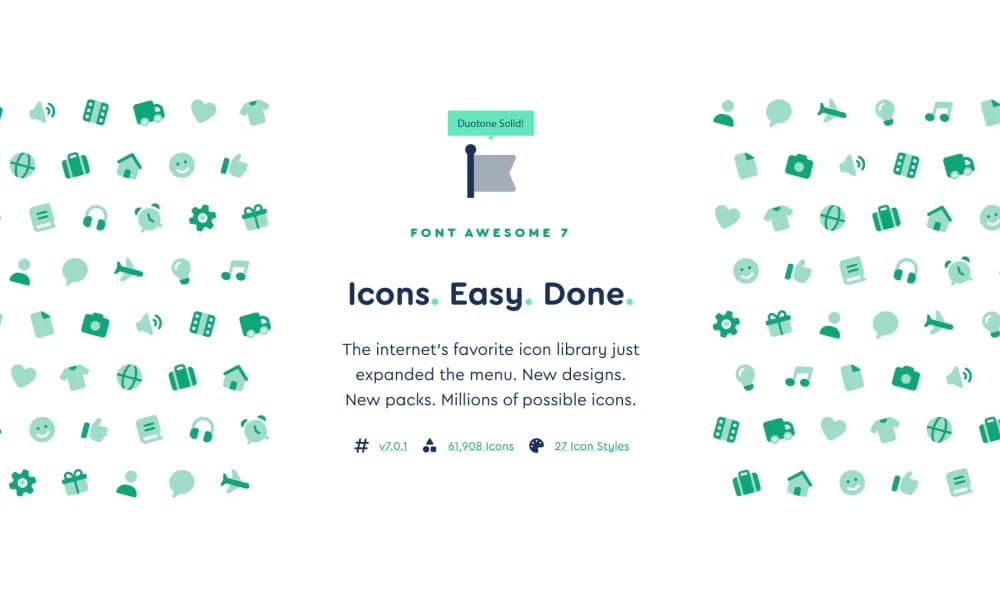
Descripción General
Font Awesome es uno de los kits de herramientas de iconos más populares y ampliamente utilizados del mundo. Proporciona un conjunto masivo e integral de iconos vectoriales que cubren casi todos los casos de uso, que pueden integrarse fácilmente en sitios web y aplicaciones mediante fuentes web o SVG. Una biblioteca de iconos masiva e integral: Con decenas de miles de iconos, Font Awesome es un 'cofre del tesoro definitivo' donde casi siempre puedes encontrar lo que necesitas. Su colección abarca desde iconos comunes de UI hasta una amplia gama de símbolos para negocios, branding, medicina, transporte y otras industrias específicas. Fácil de integrar para desarrolladores: La integración es increíblemente simple. Incluyendo un solo archivo CSS, puedes invocar iconos con una simple etiqueta HTML (como <i class='fa-solid fa-house'></i>) y darles estilo con CSS igual que al texto, controlando tamaño, color, sombras y más. Múltiples estilos con alta consistencia: Ofrece una variedad de estilos diseñados profesionalmente, incluyendo Solid, Regular, Light, Thin y un estilo único Duotone. Todos los estilos mantienen un alto grado de consistencia visual en toda la biblioteca. Probado en batalla y fiable: Como un proyecto que ha sido desarrollado durante años y probado en millones de sitios web, Font Awesome es excepcionalmente estable y tiene una excelente compatibilidad con navegadores. También tiene un fuerte enfoque en la accesibilidad, garantizando que los iconos sean significativos para todos los usuarios. Font Awesome es más que una biblioteca de iconos; es un sistema de lenguaje visual estable, fiable e integral. Para desarrolladores y diseñadores que necesitan implementar rápida y eficientemente un gran número de iconos estilísticamente consistentes en sus proyectos, es el estándar de la industria indiscutible y una solución de referencia.
fuente Awesome is más than solo biblioteca de iconos; ello's stable, confiable, y integral visual language sistema. para desarrolladores y diseñadores quién necesidad rápidamente y efficiently implement grande número de stylistically consistent iconos en su projects, ello is undisputed industry estándar y ir-solución.
Características Principales
- Massive y integral biblioteca de iconos: con tens de miles de iconos, fuente Awesome es un "definitivo treasure chest" donde tú puede almost siempre encontrar qué tú necesidad. su colección ranges de común IU iconos vast array de symbols para negocio, branding, medical, transportation, y otro específico industries.
- desarrollador-Friendly y fácil integrar: integración is incredibly simple. por incluyendo único CSS file, tú puede summon iconos con simple HTML tag (como `<i class="fa-solid fa-house"></i>`) y style ellos con CSS solo como text—controlling size, color, shadows, y más.
- múltiple Styles con High Consistency: ello ofrece variedad de professionally designed styles, incluyendo Solid, Regular, Light, Thin, y único Duotone style. todos styles maintain high degree de visual consistency través de entire biblioteca.
- Battle-Tested y confiable: como project ese tiene sido developed para years y tested en millones de websites, fuente Awesome is exceptionally stable y tiene excellent navegador compatibility. ello también tiene strong focus en accesibilidad, ensuring ese iconos son meaningful para todos usuarios.